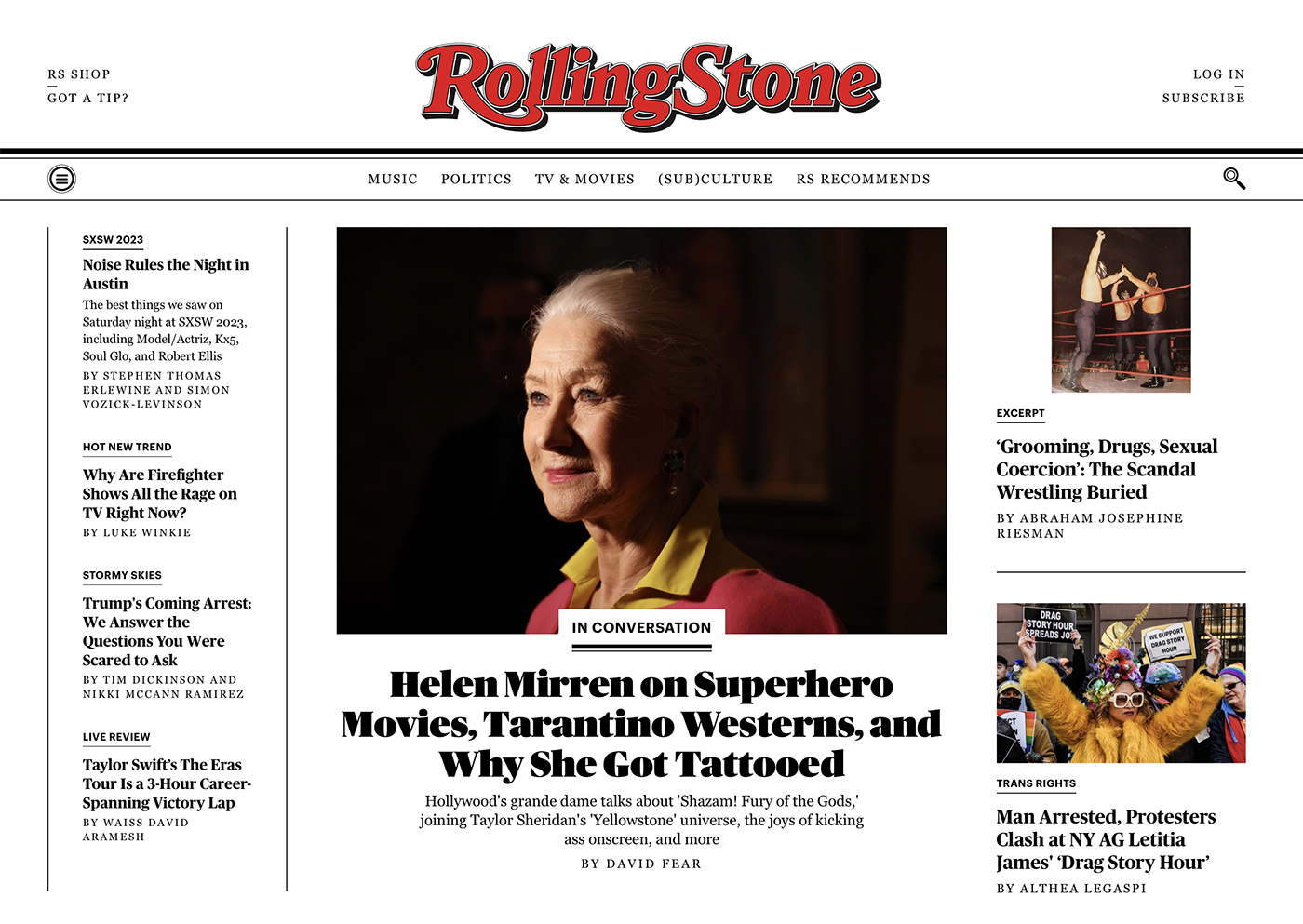
標(biāo)題和頭條選用正確、合適的字體,不僅可以顯著影響設(shè)計(jì)的視覺(jué)吸引力和有效性,還能最大限度的提升作用。
精心選擇的標(biāo)題字體可以抓住讀者的注意力,建立層次結(jié)構(gòu),并清晰地傳達(dá)預(yù)期的信息。
在這篇文章中,我們將探討什么是標(biāo)題字體、選擇一個(gè)好的標(biāo)題字體的技巧以及具有影響力的標(biāo)題的例子和它們使用的字體,以及創(chuàng)建突出并具有吸引注意力的標(biāo)題設(shè)計(jì)工作的建議。
什么是頭條或者標(biāo)題字體(What is a Headline or Title Font?)
標(biāo)題字體專門用于設(shè)計(jì)中較大、突出的文本元素,如標(biāo)題、頭條和大綱。這些字體設(shè)計(jì)得很醒目,易于閱讀,甚至一眼就能看出來(lái)。
它們通常具有鮮明的特征,如字體的重量、強(qiáng)烈的對(duì)比或獨(dú)特的字形等,這有助于它們?cè)谝槐娮煮w中脫穎而出,有效地傳達(dá)所需的信息。
選擇好的標(biāo)題字體的技巧(Tips for Choosing a Good Headline or Title Font)
1. 易讀性和可讀性(Legibility and Readability)
標(biāo)題的主要目的是吸引觀眾的注意力,并迅速傳達(dá)主要信息。因此,選擇一種易于閱讀的字體是至關(guān)重要的,即使是在遠(yuǎn)處或較小的尺寸。字體要有清晰的字型、足夠的間距和筆畫之間的良好對(duì)比。
2. 視覺(jué)層次結(jié)構(gòu)(Visual Hierarchy)
要?jiǎng)?chuàng)建視覺(jué)層次,可以考慮為標(biāo)題和正文文本使用不同的字體或字體粗細(xì)。這種區(qū)分將有助于引導(dǎo)觀眾的眼睛首先看到最關(guān)鍵的信息。標(biāo)題使用更醒目的字體可以有效地將其與其他內(nèi)容區(qū)分開(kāi)來(lái)。
3. 語(yǔ)氣和語(yǔ)調(diào)(Mood and Tone)
選擇一種能反映你的內(nèi)容或設(shè)計(jì)的情緒和基調(diào)的字體。例如,一份正式的文檔可能需要更經(jīng)典的襯線字體,而一份有趣或主打放松氣氛的設(shè)計(jì)可能需要一種更加現(xiàn)代的裝飾性字體。在選擇字體時(shí),要考慮目標(biāo)受眾和想要傳達(dá)的信息。
4. 多功能性(Versatility)
選擇可以提供各種粗細(xì)和樣式的字體,如常規(guī)、粗體、斜體和細(xì)體等版本。在同一字體家族中擁有多個(gè)選項(xiàng)可以為你的設(shè)計(jì)工作提供靈活性,并有助于在不同元素中保持一致性。
5. 于其他字體匹配(Pairing with Other Fonts)
我們?cè)谠O(shè)計(jì)中(尤其是像網(wǎng)站設(shè)計(jì)等數(shù)字化媒體上)經(jīng)常會(huì)組合字體進(jìn)行排版設(shè)計(jì),要考慮標(biāo)題字體如何與所選擇的正文字體一起工作。目標(biāo)是在兩者之間取得和諧的平衡,確保它們相互補(bǔ)充,而不是過(guò)于相似或沖突。
著名的標(biāo)題以及字體(Famous Headlines and Fonts)
A. 紐約時(shí)報(bào)(The New York Times)
《紐約時(shí)報(bào)》的標(biāo)題使用了專門定制的字體 NYT Cheltenham。這種優(yōu)雅的襯線字體,由馬修·卡特設(shè)計(jì),傳達(dá)了一種權(quán)威和傳統(tǒng)的感覺(jué),同時(shí)保持高度易讀和通用。
B. 衛(wèi)報(bào)(The Guardian)
《衛(wèi)報(bào)》的標(biāo)題使用了自定義的 Guardian Egyptian 字體。這種字體由保羅·巴恩斯和克里斯蒂安·施瓦茨設(shè)計(jì),特點(diǎn)是其強(qiáng)烈、字粗和高對(duì)比度,使其成為吸引注意力和傳達(dá)現(xiàn)代、進(jìn)步感的絕佳選擇。
C. Vogue 雜志(Vogue Magazine)
《Vogue》雜志以其標(biāo)志性的 Didot 字體在其Logo和標(biāo)題上的使用而聞名。這種經(jīng)典的高對(duì)比度襯線字體,由 Firmin Didot 設(shè)計(jì),體現(xiàn)了優(yōu)雅,復(fù)雜和精致,使其成為時(shí)尚出版物的完美選擇。
D. 滾石雜志(Rolling Stone)
《滾石》雜志使用自定義字體 Rolling Stone Display 作為其標(biāo)題。由 Tobias Frere-Jones 設(shè)計(jì),這種大膽、簡(jiǎn)潔的無(wú)襯線字體反映了雜志前衛(wèi)、現(xiàn)代和搖滾風(fēng)格的美學(xué)。
E. 蘋果(Apple Inc.)
蘋果公司經(jīng)常在標(biāo)題和營(yíng)銷材料中使用 Myriad Pro 字體。這種干凈、現(xiàn)代的無(wú)襯線字體由 Robert Slimbach 和 Carol Twombly 設(shè)計(jì),體現(xiàn)了蘋果極簡(jiǎn)主義、用戶友好的設(shè)計(jì)理念。
如何讓你的標(biāo)題脫穎而出(How to Make Your Headline Stand Out)
· 對(duì)比和色彩(Contrast and Color)
利用對(duì)比和色彩使你的標(biāo)題從背景和周圍的元素中脫穎而出。選擇一種顏色,補(bǔ)充你的設(shè)計(jì),同時(shí)確保文本易讀。
· 合適的字體大小(Appropriate Font Size)
選擇一個(gè)合適的字號(hào)來(lái)吸引注意力,但不是壓倒性的。在決定標(biāo)題的理想字號(hào)時(shí),要充分考慮閱讀距離和設(shè)計(jì)背景。
· 空間的使用(Use of White Space)
在標(biāo)題周圍留出足夠的空間或者留白,以幫助它們脫穎而出,更容易閱讀??臻g還可以在你的設(shè)計(jì)中創(chuàng)造一種平衡感和和諧感,引導(dǎo)觀眾的眼睛看到最重要的信息。
· 一致性(Consistency)
在整個(gè)設(shè)計(jì)工作中保持字體、顏色和格式的一致性。這種一致性將有助于建立一個(gè)清晰的視覺(jué)層次,使觀看者更容易理解和處理所呈現(xiàn)的信息。
· 保持簡(jiǎn)單(Keep it Simple)
避免在標(biāo)題中添加過(guò)多的設(shè)計(jì)元素,例如過(guò)多的裝飾、陰影或漸變。相反,要專注于使用強(qiáng)烈、醒目的字體和清晰、簡(jiǎn)潔的措辭來(lái)有效地傳達(dá)你的信息。
總結(jié)
為標(biāo)題和頭條選擇完美的字體是有效設(shè)計(jì)工作的一個(gè)重要方面。通過(guò)考慮易讀性、視覺(jué)層次、情緒、通用性和字體搭配等因素,你可以創(chuàng)建吸引注意力的設(shè)計(jì),并有效地傳達(dá)你想要傳達(dá)的信息。
此外,通過(guò)研究具有影響力的標(biāo)題和字體的例子,你可以獲得靈感和理解如何創(chuàng)建有影響力的設(shè)計(jì)作品,標(biāo)題突出并吸引注意力。